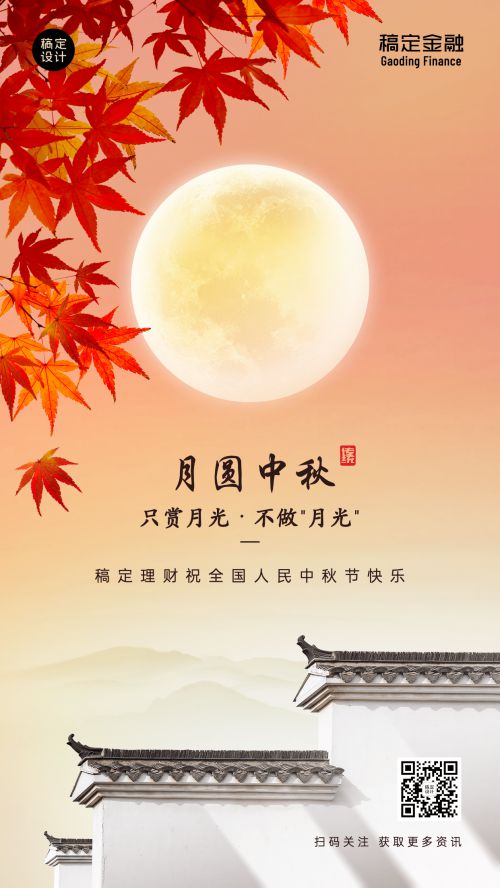
站酷酷黑
字库品牌: 站酷字体
### 站酷酷黑:力量感与现代美学兼具的免费商用黑体 **站酷酷黑**是由站酷字体推出的**创意黑体**,以**粗犷有力**的笔画和**方正宽博**的字形著称,完美融合**力量、现代、端庄、简约**四大核心风格,支持**免费商用**,是设计领域的实用之选。 **站酷酷黑**字形方正,中宫宽博,字重饱满粗壮,笔画粗细均匀,展现出沉稳厚重的视觉张力。其笔型设计极具特色:以**直角为基调**,搭配利落的**斜切处理**,方头笔画与断开式连接结构,既保留黑体的端庄辨识度,又通过细节修饰增强设计感与精致度。重心居中的排布与宽扁字面设计,使文字排版组合醒目大气,尤其适合标题、广告、海报等需要视觉冲击的场景。 作为免费商用字体,**站酷酷黑**包含3500个常用简体汉字、52个英文字母及10个阿拉伯数字,字符覆盖满足日常设计需求。由胡晓波发起,字游工作室及学员联合打造,自2016年站酷十周年发布以来,便以独特的工业风美学成为设计师青睐的标题字体,兼具实用价值与艺术表现力。 无论是追求现代极简风格,还是需要传递强劲视觉力量,**站酷酷黑**都能以其粗粝而不失精致的笔触,为作品注入独特魅力。